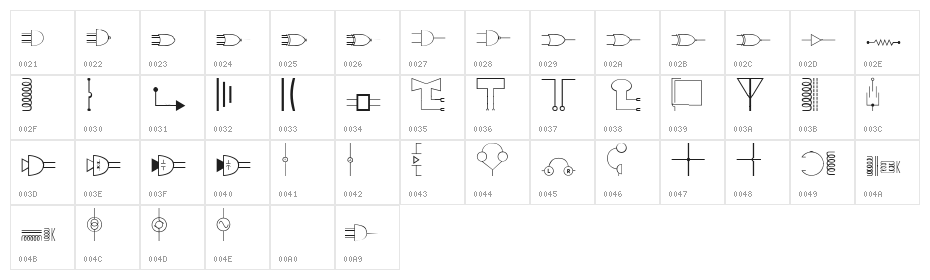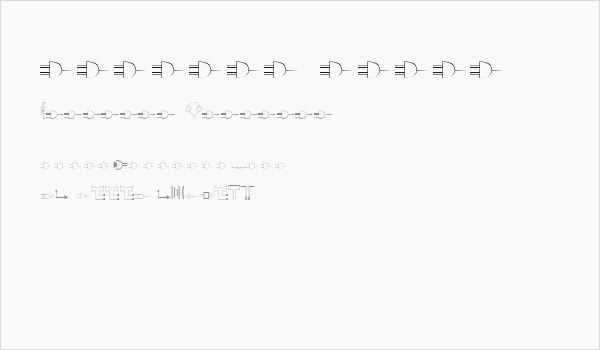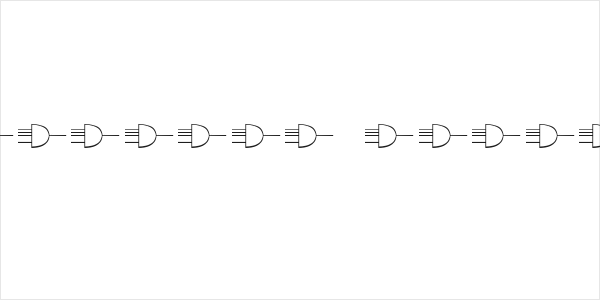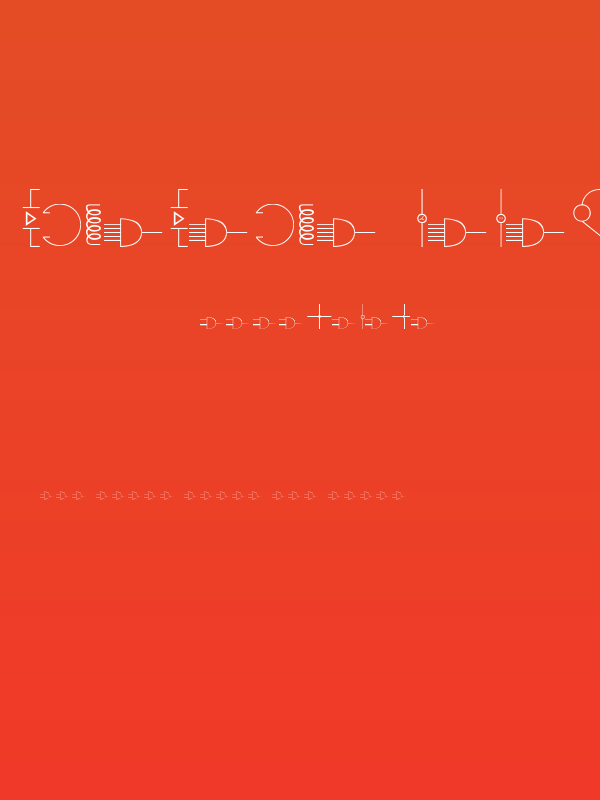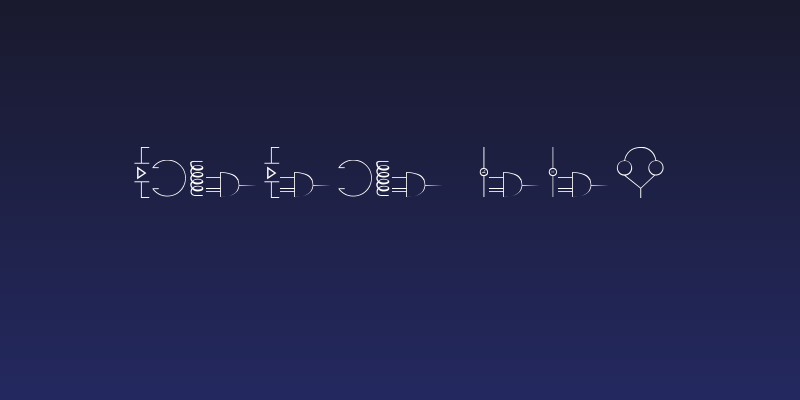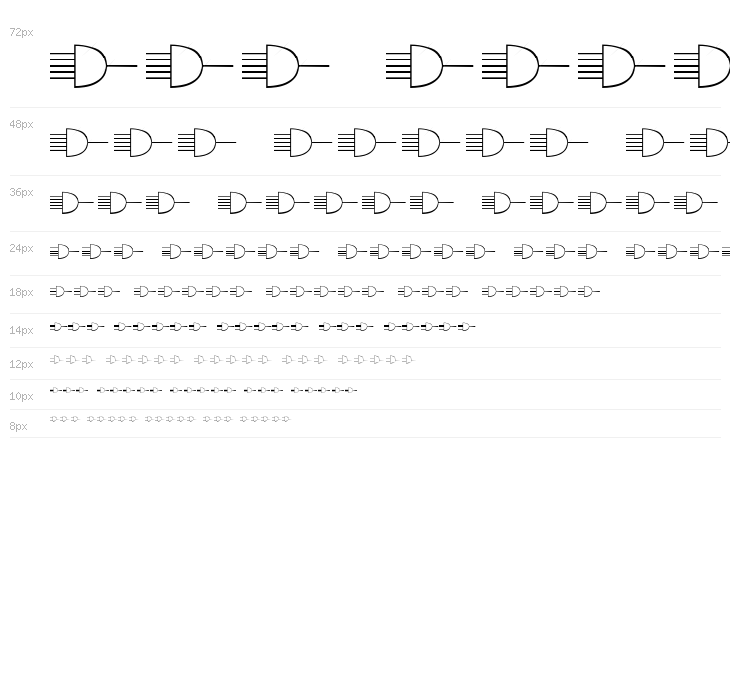
circuit board Font
tricky
| Gesamtstil | Decorative, Technical, Futuristic |
| Anwendungsfall | Logos, Headlines, Posters, Themed Graphics |
| Vorgeschlagene Projekte | Technology branding, science fiction posters, electronics event flyers, educational materials for electronics, themed logos. |